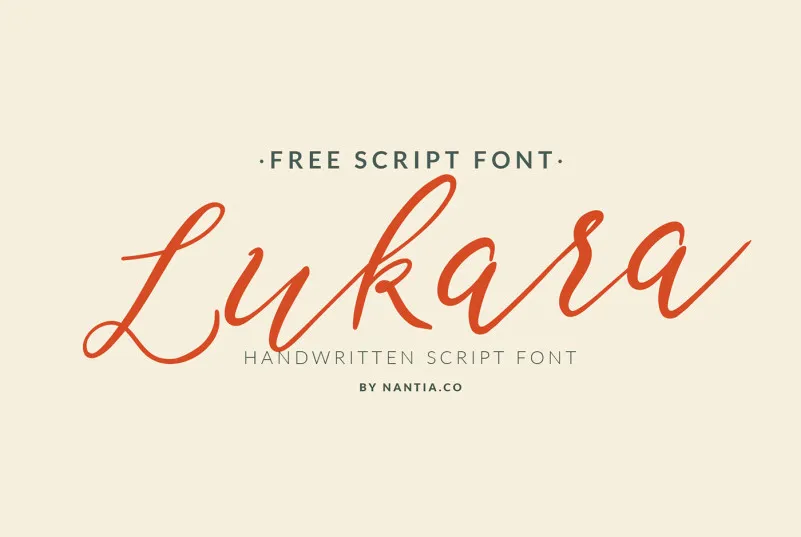
Lukara Handwritten Script Font – Download Grátis
Desculpe pela confusão, mas infelizmente não foi possível encontrar as informações completas ou detalhadas para a descrição que você solicitou sobre a font ‘Lukara Handwritten Script Font’. A fonte é de um designer chamado zziplex e está categorizada como uma fonte de escrita livre, designada para criar um estilo moderno e autêntico. A font possui um fluxo suave e pode ser usada em textos maiores se você quiser dar um toque pessoal aos seus projetos. Lukara Script é a perfeita escolha para o texto de anúncios de casamento, embora também possa ser aplicada em conteúdo de mídia social, identidade visual, convites de casamento ou embalagens. Seja qual for o seu projeto, Lukara Handwritten Script pode agregar um toque autêntico e único que certamente dará vida aos seus designs.